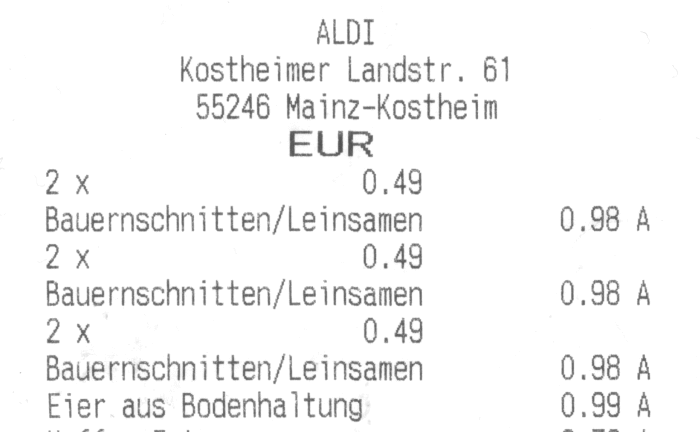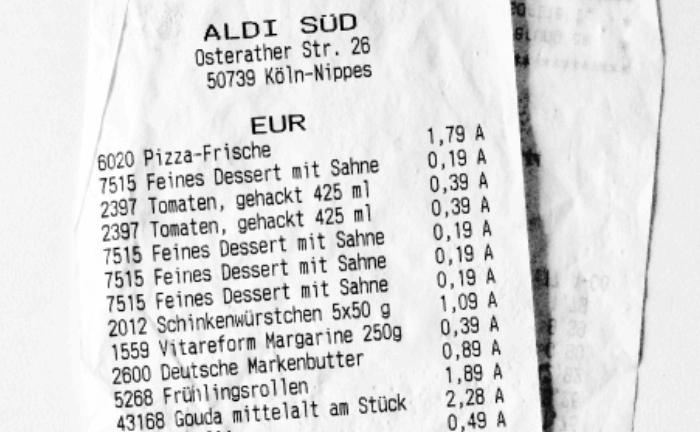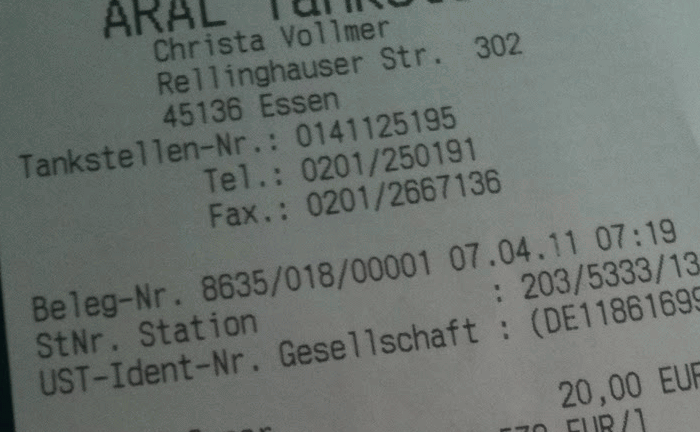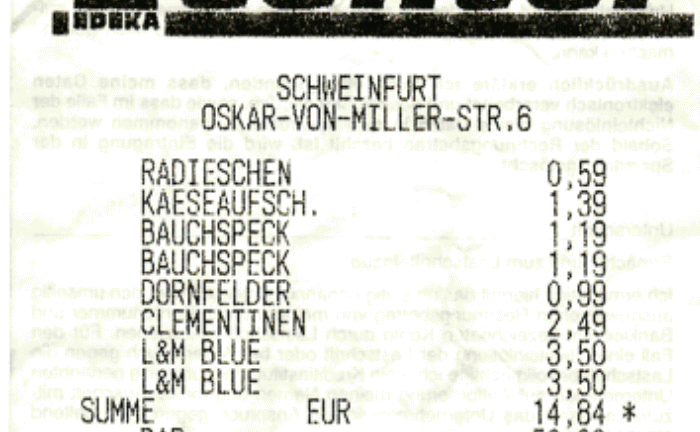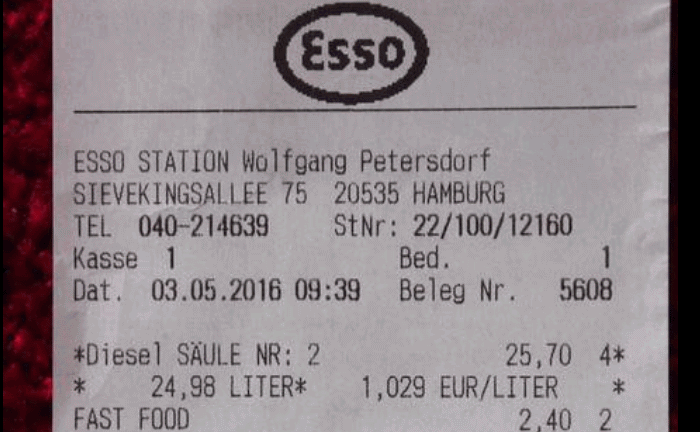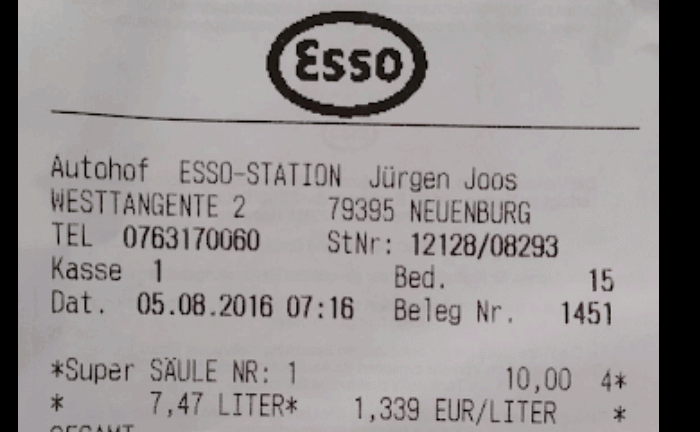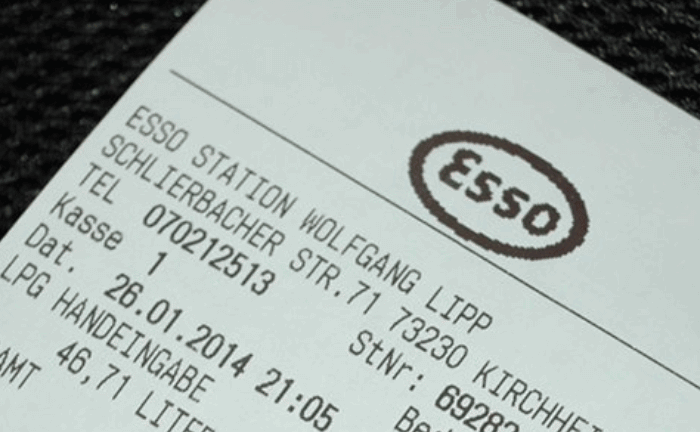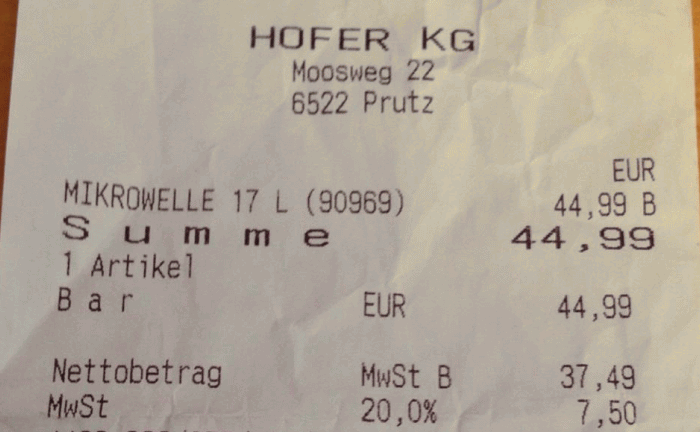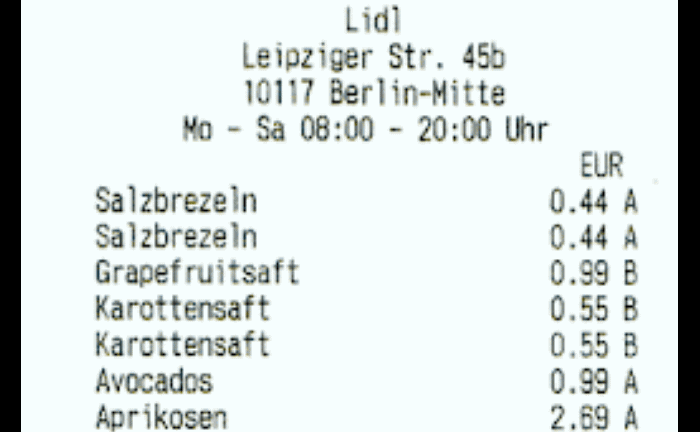
Die gebräuchlichste Kassenbon-Schriftart von Registrierkassen
oft auf Kassenbelegen, Kundenkopien oder Rechnungspapieren zu sehen, die von Thermodruckern verwendet werden
Die gebräuchlichste Kassenbon-Schriftart von Registrierkassen
auf dem Computerbildschirm angezeigt⤴
gedrucktes Sample von der Schriftart⤴